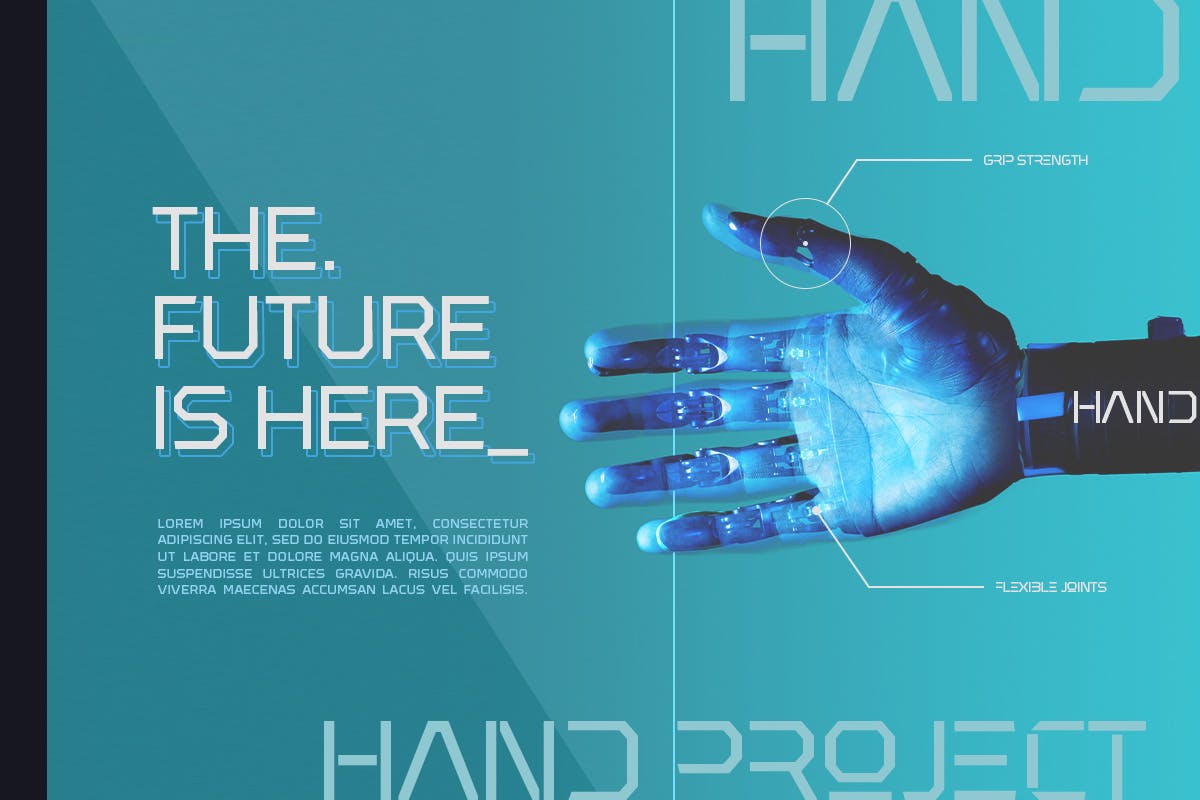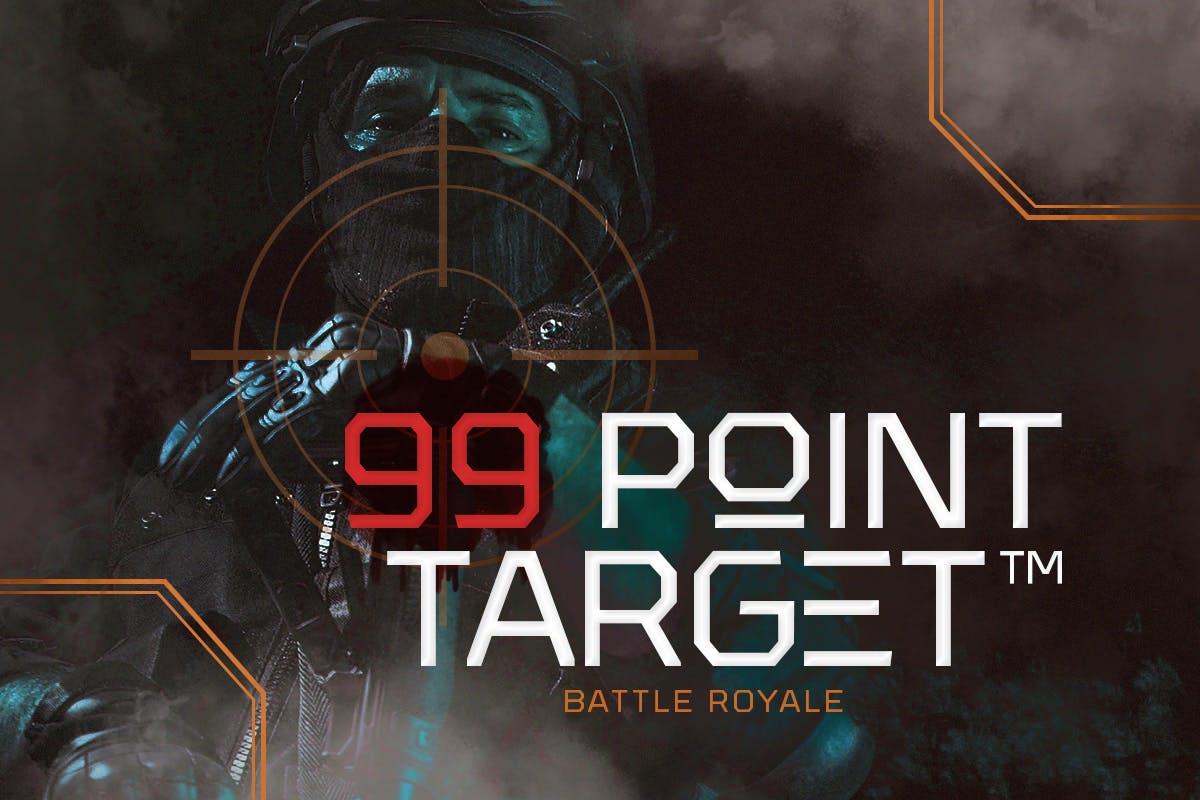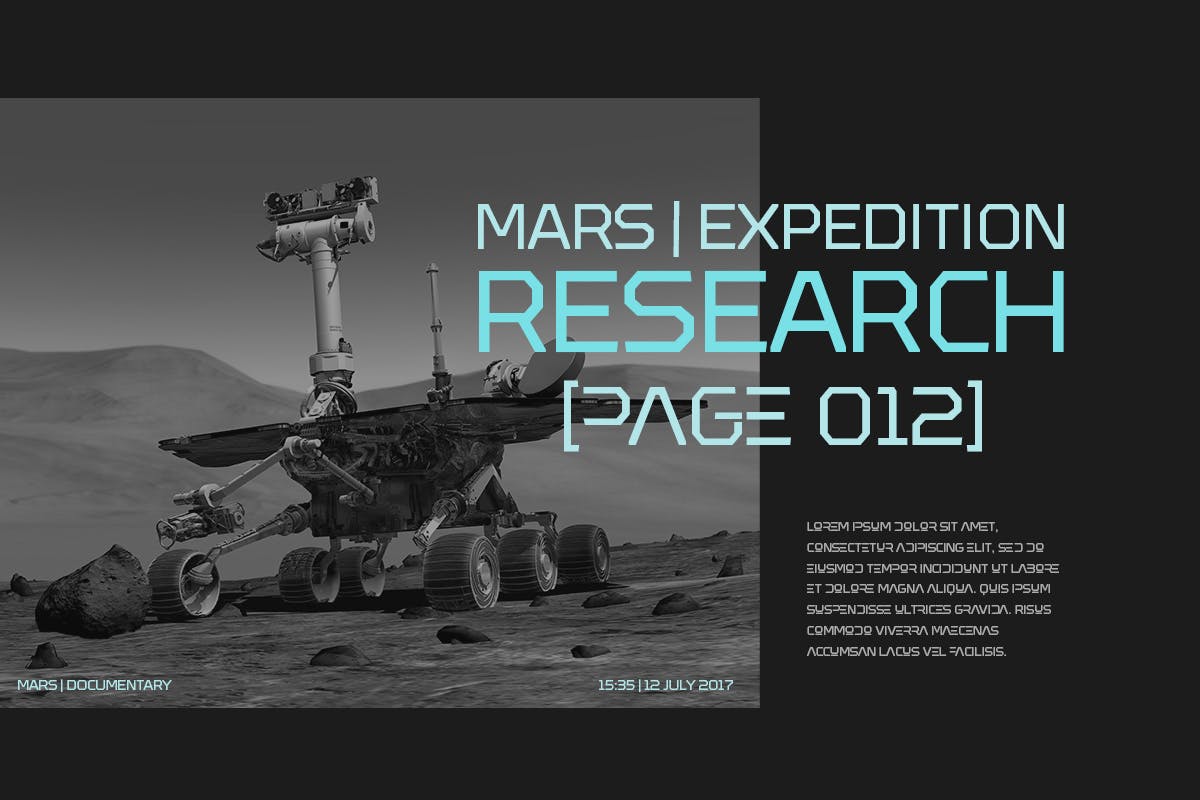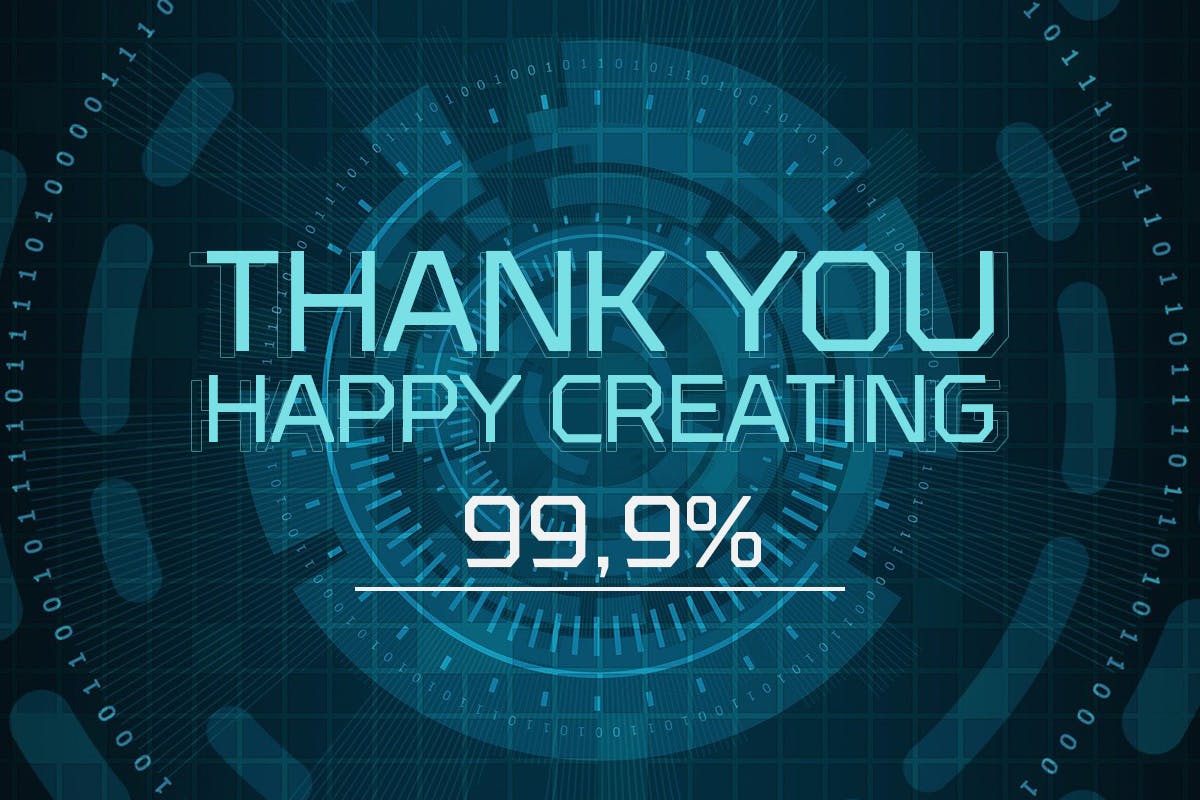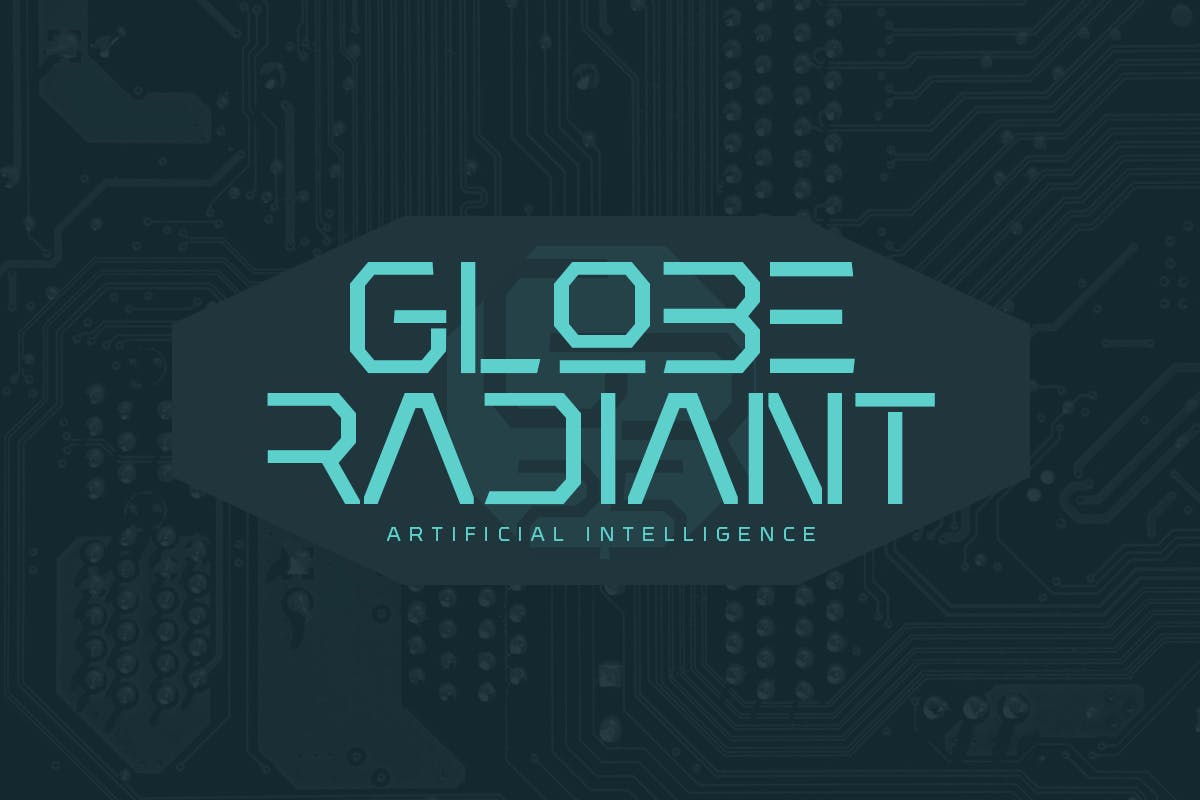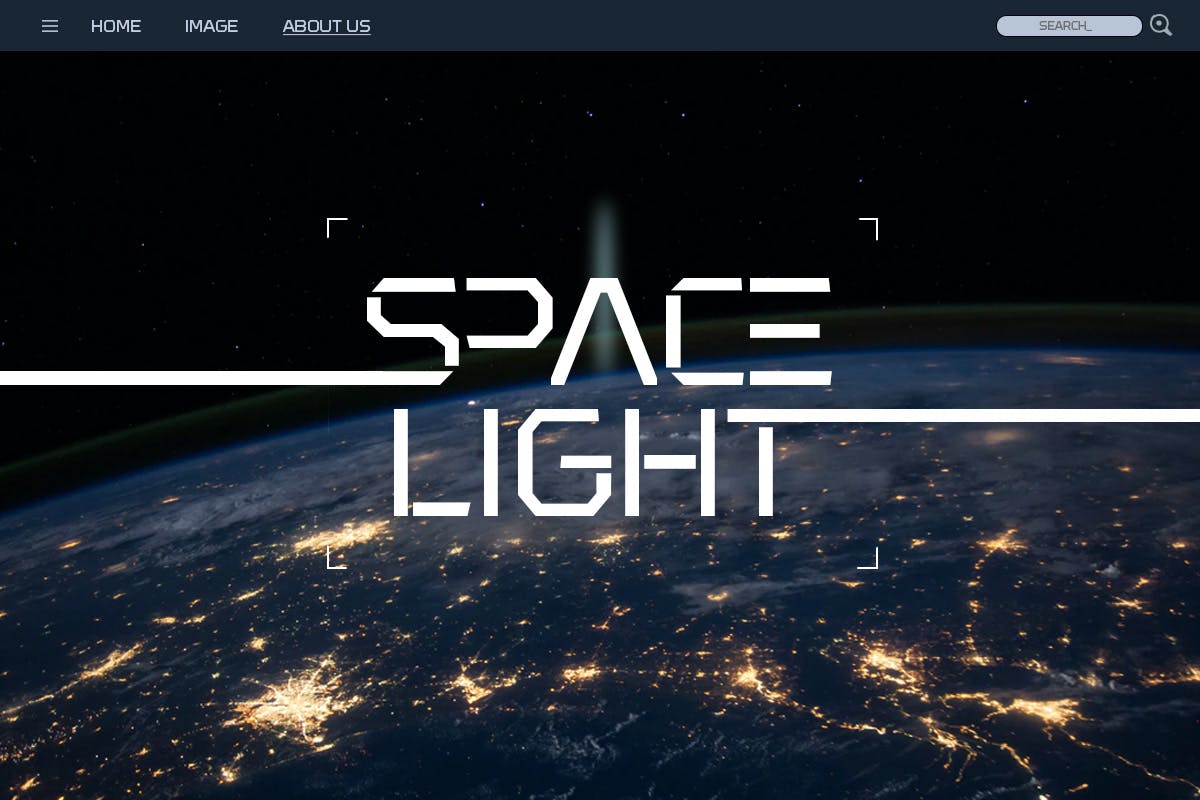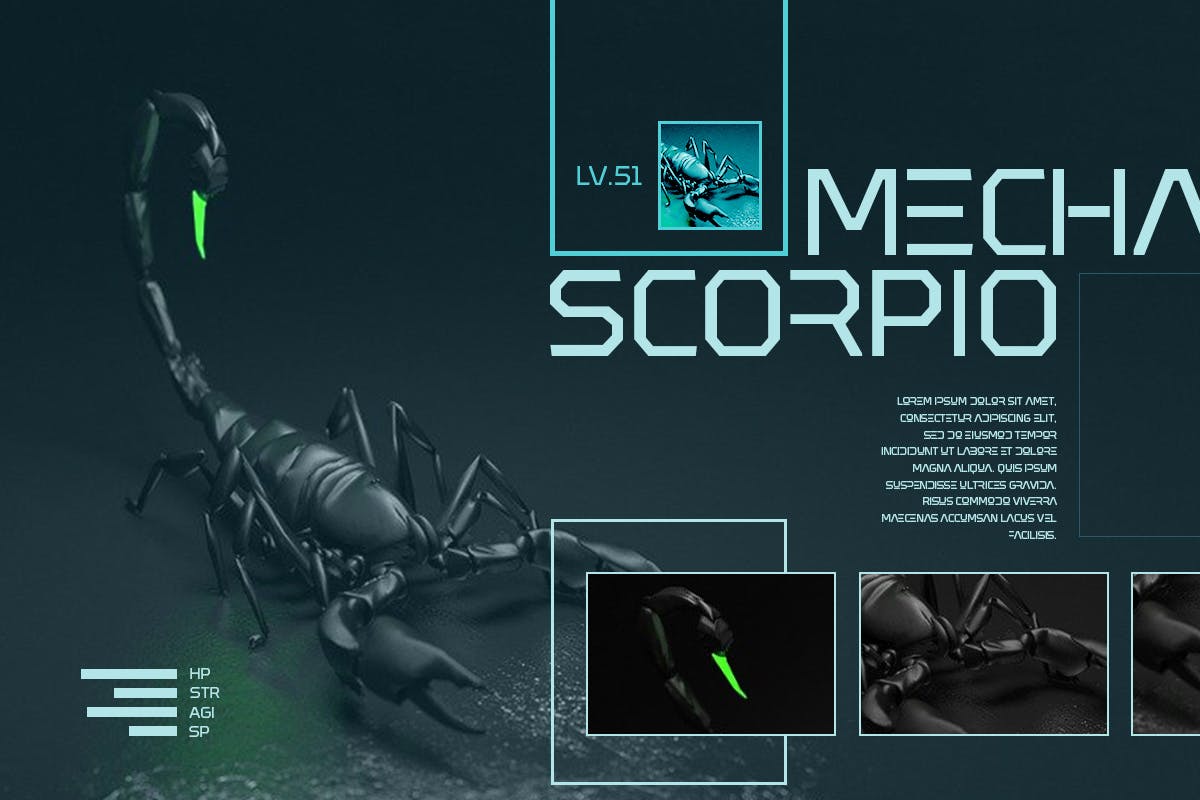
فونت لوگوی Rosterian Futuristic Logotype، با سبک استنسیل و طراحی مدرن، برای تمهای آیندهنگر مناسب است و همچنین برای طراحیهای مربوط به دنیای فضایی بسیار عالی میباشد.